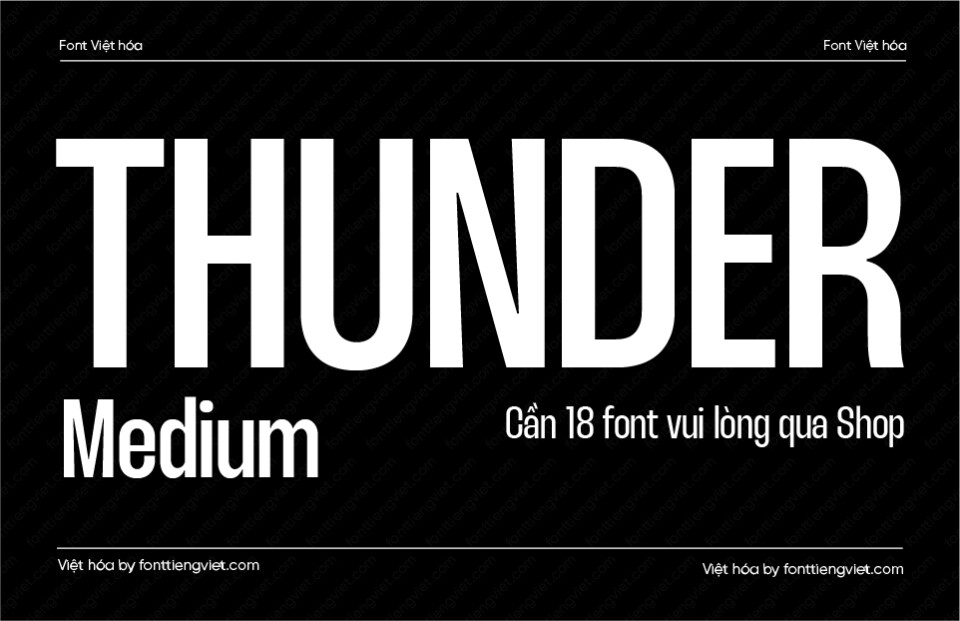
Font Việt hóa 1FTV VIP Thunder Medium
Giới thiệu về Font Việt hóa 1FTV VIP Thunder Medium
Trong thế giới đồ họa hiện đại, việc tìm kiếm một bộ Font Miễn Phí chất lượng và hỗ trợ tiếng Việt đầy đủ luôn là ưu tiên hàng đầu của các nhà thiết kế. Font Việt hóa 1FTV VIP Thunder Medium xuất hiện như một giải pháp hoàn hảo, mang đến sự kết hợp tinh tế giữa vẻ ngoài mạnh mẽ và sự linh hoạt trong sử dụng. Đây là một phông chữ thuộc phong cách Sans Serif hiện đại, được tinh chỉnh kỹ lưỡng về khoảng cách và các dấu thanh đặc trưng của ngôn ngữ tiếng Việt. Với độ dày vừa phải (Medium), phông chữ này không quá mảnh mai nhưng cũng không quá thô kệch, tạo nên một sự cân bằng tuyệt vời cho thị giác người xem. Đối với các bạn học sinh, sinh viên hay giáo viên đang tìm kiếm sự đổi mới cho các bài thuyết trình, sản phẩm thiết kế này chính là lựa chọn không thể bỏ qua để nâng tầm giá trị thẩm mỹ.
Những đặc điểm nổi bật của Font Việt hóa 1FTV VIP Thunder Medium
Cấu trúc đường nét hiện đại và chuyên nghiệp
Đặc trưng lớn nhất của Font Việt hóa 1FTV VIP Thunder Medium chính là các đường nét dứt khoát và hình khối rõ ràng. Các ký tự được thiết kế với tỷ lệ chuẩn xác, giúp việc đọc nội dung trở nên dễ dàng ngay cả ở kích thước nhỏ. Điểm đặc biệt của phiên bản Việt hóa này là hệ thống dấu câu được đặt vị trí rất tự nhiên, không gây cảm giác rời rạc hay lỗi font thường gặp ở các bộ chữ nước ngoài chưa qua xử lý. Điều này giúp các sản phẩm thiết kế giữ được sự đồng nhất và chuyên nghiệp cao nhất.
Tính ứng dụng đa dạng trong nhiều lĩnh vực
Không chỉ giới hạn trong thiết kế đồ họa chuyên nghiệp, phông chữ này còn cực kỳ hữu ích trong môi trường học đường. Bạn có thể sử dụng nó để làm tiêu đề cho các báo cáo, thiết kế bìa sách, hoặc làm nội dung chính cho các tấm poster tuyên truyền của trường lớp. Font Việt hóa 1FTV VIP Thunder Medium mang lại cảm giác tin cậy, năng động và tràn đầy sức sống, rất phù hợp với tinh thần của thế hệ trẻ. Sự tối giản của nó cũng giúp người xem tập trung tối đa vào thông điệp mà bạn muốn truyền tải mà không bị xao nhãng bởi các chi tiết rườm rà.
Lợi ích khi sử dụng Font Việt hóa 1FTV VIP Thunder Medium
Kết luận về bộ font chữ độc đáo này
Tóm lại, Font Việt hóa 1FTV VIP Thunder Medium là một bộ phông chữ không thể thiếu trong bộ sưu tập của các designer và những người yêu thích cái đẹp. Với sự kết hợp hoàn hảo giữa công năng và thẩm mỹ, nó chắc chắn sẽ giúp các ý tưởng của bạn trở nên sống động và thu hút hơn bao giờ hết. Nếu bạn đang tìm kiếm một nguồn tài nguyên Font Miễn Phí, Font Việt Hóa, Font Việt hóa 1FTV VIP Thunder Medium chất lượng cao để phục vụ cho công việc và học tập, hãy trải nghiệm ngay hôm nay. Hy vọng rằng phông chữ này sẽ khơi nguồn cảm hứng sáng tạo bất tận cho bạn trong mọi dự án thiết kế sắp tới.